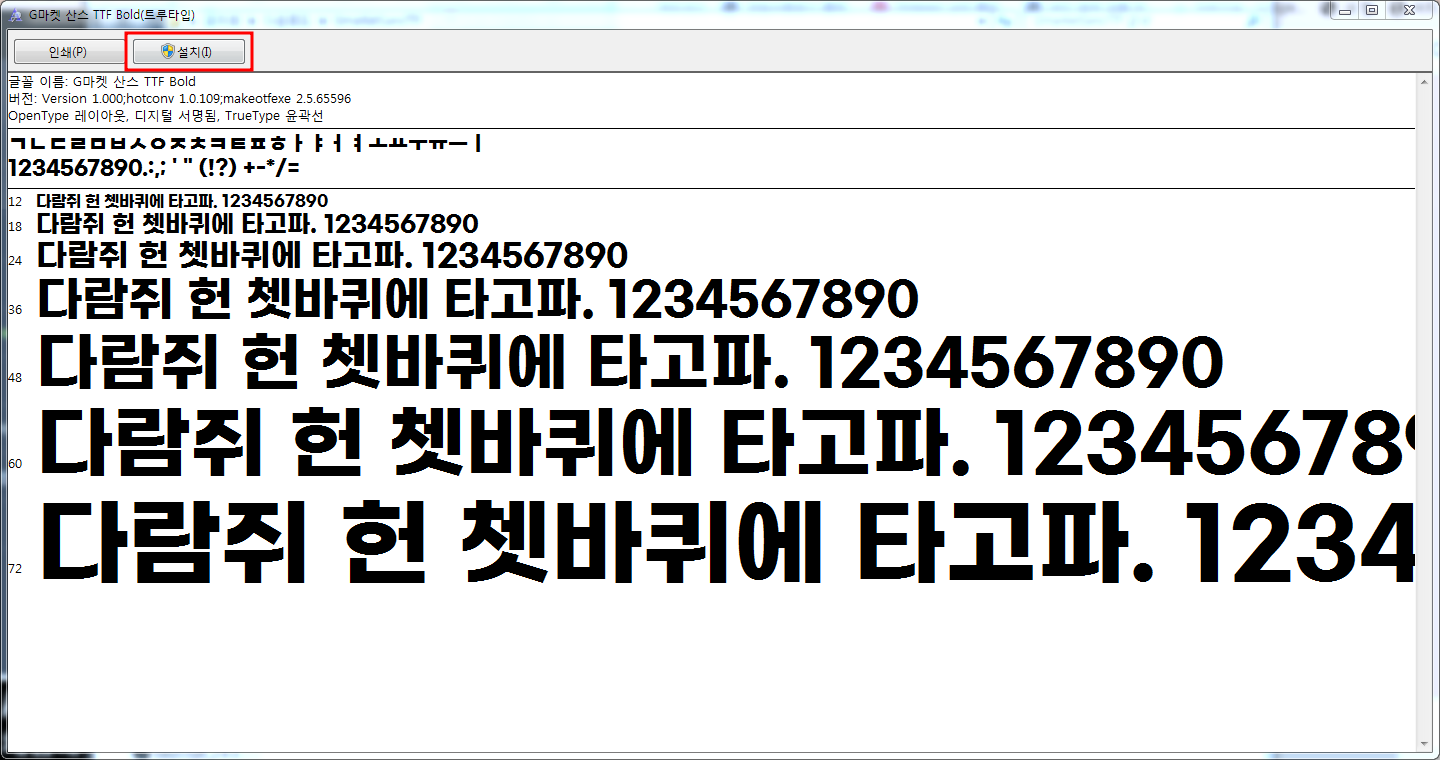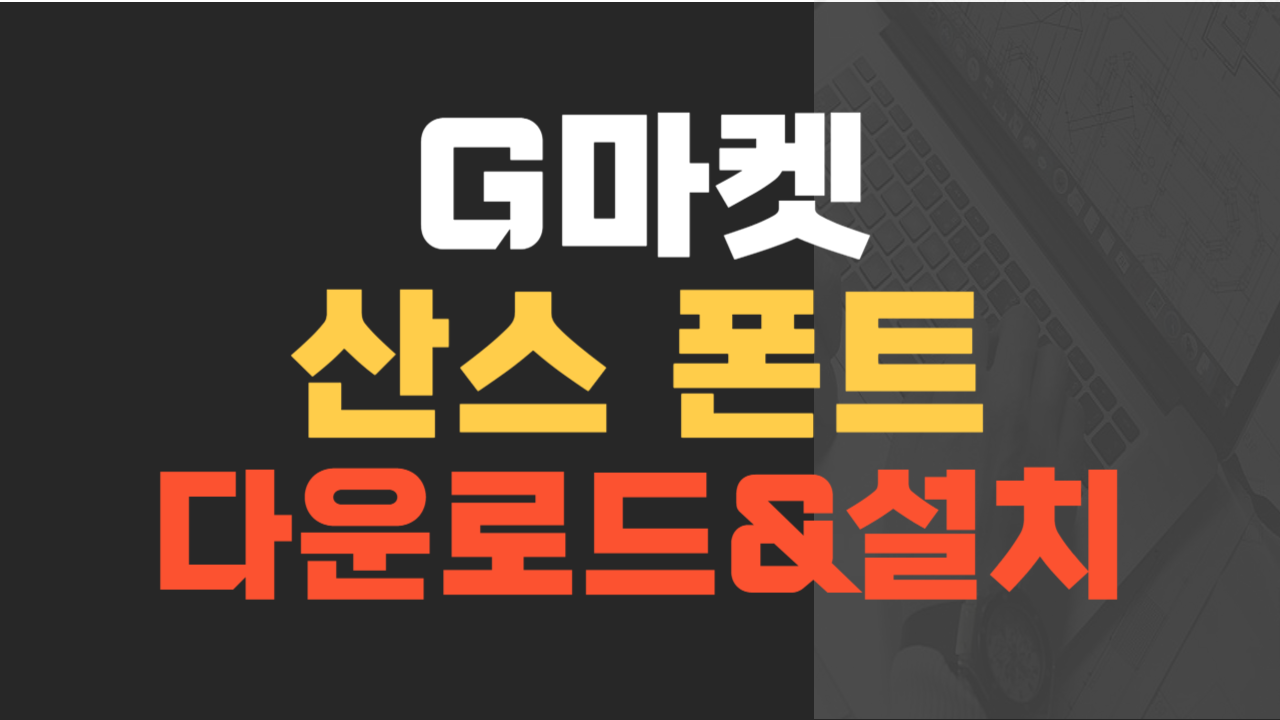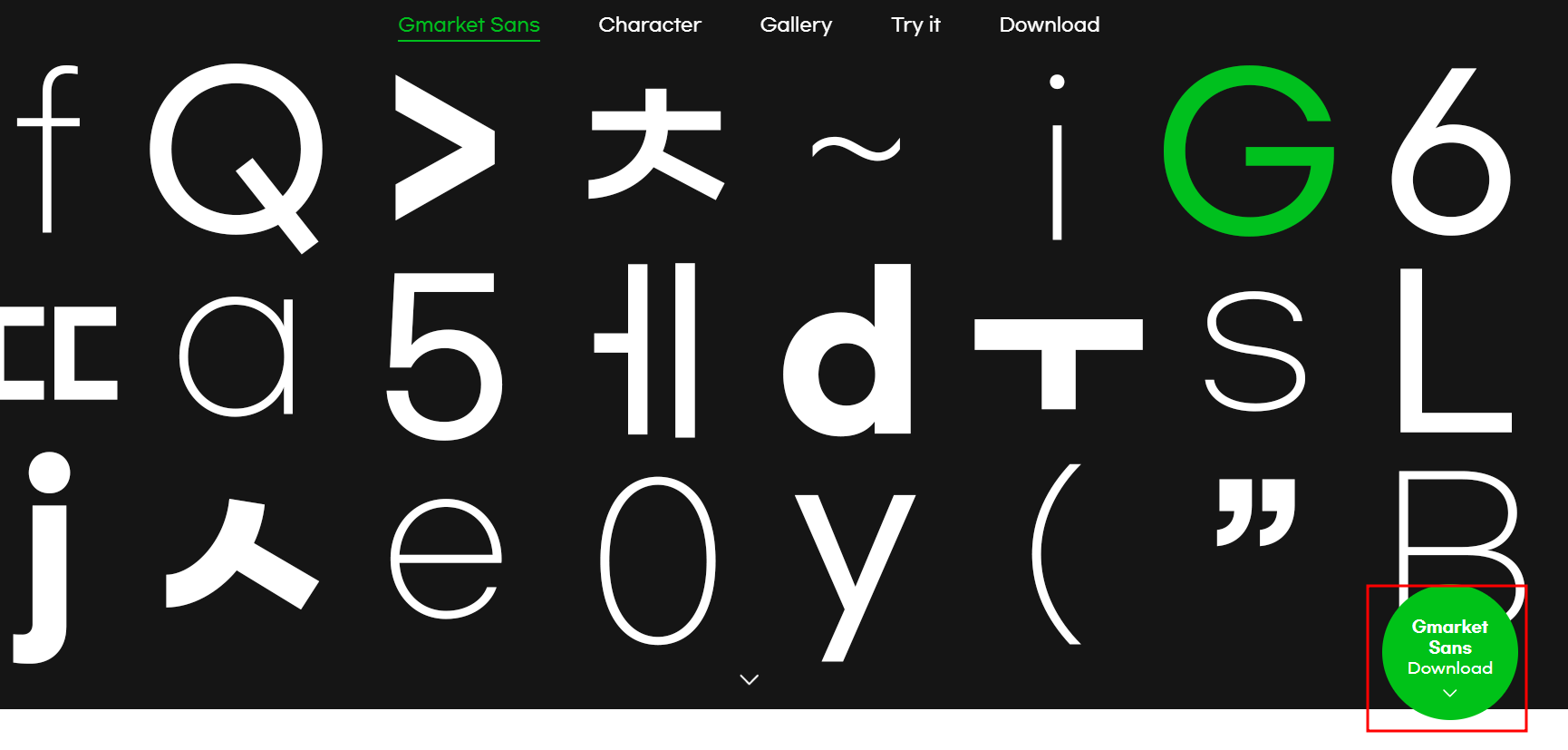
G마켓 산스 폰트 지마켓 산스체 다운로드 & 설치 방법
G마켓 산스 폰트는 우리가 잘 아는 G마켓에서 무료로 배포하고 있는 글자체입니다. G마켓 산스 폰트는 무료임에도 글자 폰트의 가독성이 매우 좋아서 블로그나 유튜브의 썸네일을 제작할 때 많이 사용되고 있습니다. 이번 포스티에서는 가독성이 매우 좋은 G마켓 산스 폰트를 무료로 다운로드하고 설치하는 방법에 대해 설명하겠습니다. 블로그나 유튜브를 운영하시는 여러분들도 한번 사용해 보시길 추천드립니다.